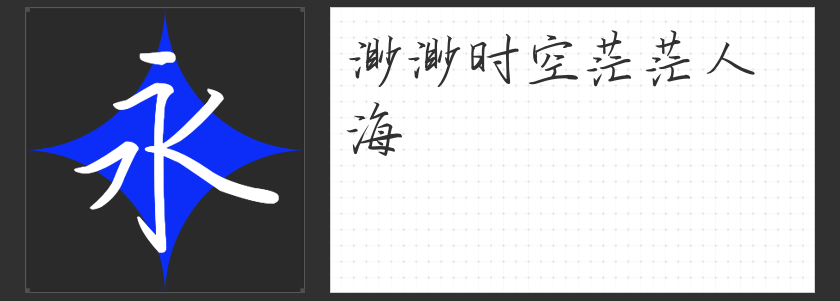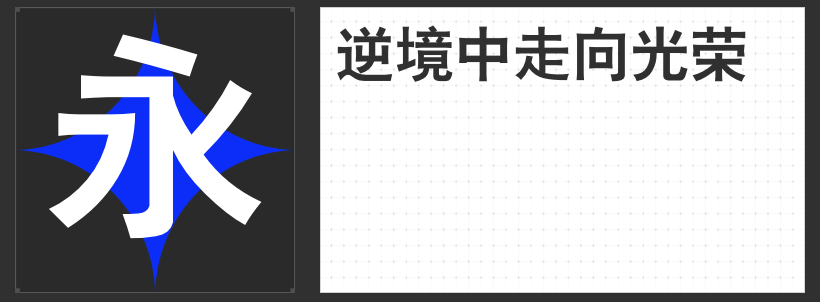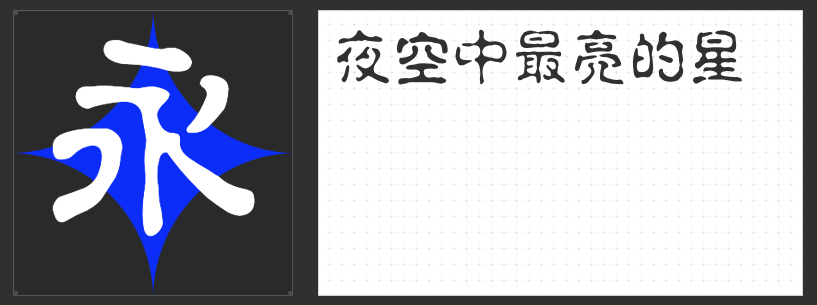
媒体设计中的点睛之笔:四款专业字体的视觉美学解析
在媒体设计的视觉语言中,字体不仅是信息传递的载体,更是塑造品牌调性的核心元素。以下四款各具特色的专业字体,以其独特的设计逻辑与美学价值,为设计师提供了多元化的表达可能。
一、云书法惠中行书体
这款行书字体以楷书为骨、草书为魂,在工整与灵动间找到完美平衡。其笔画间自然流露的勾挑牵丝,既保留了传统书法的书写韵律,又通过数字化处理强化了视觉连贯性。相较于传统行书,它弱化了锋芒毕露的锐度,转而以圆润的转折与舒展的布局传递温润气质,尤其适合需要传递文化底蕴与人文关怀的媒体场景,如文化纪录片字幕、艺术展览导视等。
二、励字大黑简繁
作为无衬线字体的强化版,这款字体以超粗笔画构建出极具冲击力的视觉框架。正方形的字面比例与横平竖直的笔画结构,赋予其稳固的视觉重心,而末端钝化的撇捺设计则消解了粗黑体常见的生硬感。在需要强调权威性与现代感的场景中,如科技产品发布会主标题、金融数据可视化图表,其简洁有力的形态能瞬间抓住观众注意力。
三、励字水柱简繁
突破传统字体构造逻辑,这款设计将水滴的流动感转化为笔画语言。每一笔都似由液态墨珠自然衔接而成,既保留了无衬线字体的清晰可读性,又通过微妙的弧度变化注入灵动气息。在运动品牌广告、儿童教育类媒体内容中,其活泼而不失精致的特质能有效拉近与受众的距离。
四、励字光明简 超黑
这款超粗装饰体以太阳的圆形意象为灵感,通过全弧线笔画构建出充满张力的视觉体系。斜切处理的横笔末端与开口字底的创新设计,在保持字体整体性的同时增添了锐度。其高灰度均匀分布与可拉伸特性,使其成为户外广告、数字媒体标题设计的理想选择,既能承载远距离观看的视觉重量,又能在特写镜头下展现细节层次。
这四款字体通过差异化的设计语言,共同拓展了媒体设计的表达边界。无论是追求文化深度、力量感、动态美还是未来主义,设计师都能从中找到契合项目需求的视觉解决方案。